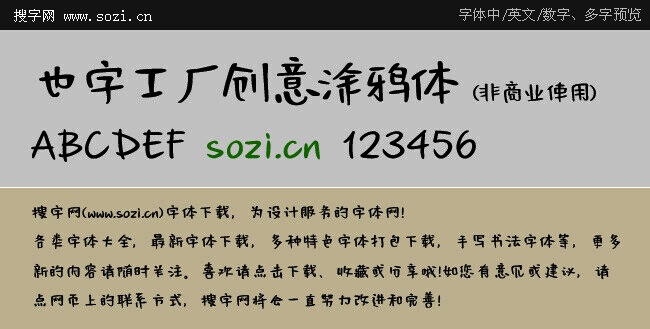
也字工厂创意涂鸦体
搜字网给大家提供一款也字工厂创意涂鸦体(非商业使用)中文字体下载,也字工厂创意涂鸦体是一款手写风格的卡通字体,字体带有书法笔触,字形富于变化,非常可爱。适合应用于海报设计、包装设计、网页设计等应用(此字体为个人非商用版,商用可以联系:官方网址:https://yefont.com/home,联系方式:13798980448)。